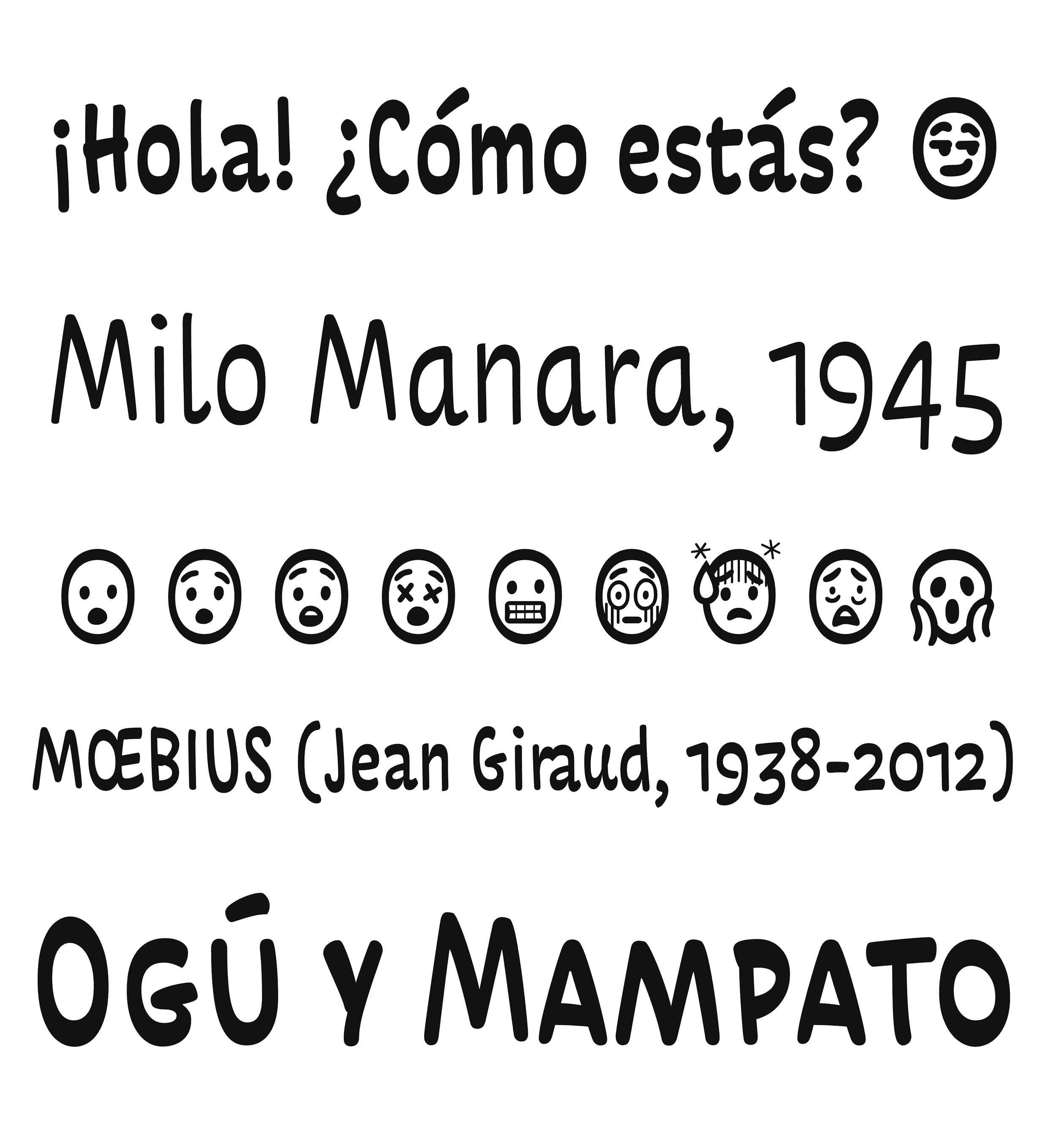
| Descripción | RunRun es una familia tipográfica austera para textos manuscritos con un ritmo relajado, compuesta por tres pesos con grosores sutilmente diferentes, también disponible como fuente variable. A pesar de su aspecto informal, RunRun fue diseñada para funcionar bien en textos de lectura inmersiva, como novelas gráficas, cómics o libros infantiles, por lo que cuenta con un amplio conjunto de glifos que incluye muchos refinamientos tipográficos, como versalitas, diferentes figuras, ligaduras y alternativas contextuales. Junto con esto, añadimos un conjunto de emojis de caras para complementar las aplicaciones y el estado de ánimo de la familia tipográfica ;-) Run Run es el nombre que se le da en Chile a Hymenops perspicillatus, un ave nativa del centro-sur de Sudamérica; también es el título de una canción popular de Violeta Parra (Run Run se fue pa'l norte / Run Run went to the north), y el nombre de un juego infantil que utiliza un botón y lana que se hila tirando de ella. |
| Clasificación | Títulos, Dingbats |
| Familia(s) | Regular, Medium, Bold |